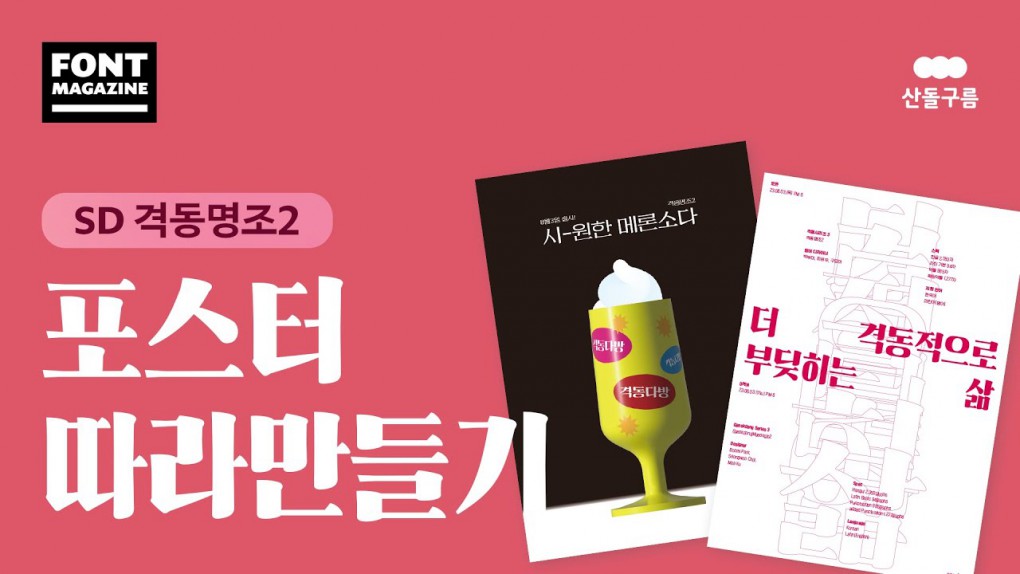
「SD 격동명조2」 출시 기념, 포스터 만들기 윗미~
‘격동’이라는 단어에서부터 가슴이 웅장해지는 분들, 많으시죠?
8월의 시작과 함께 반가운 소식을 전해드려요. 바로 「SD 격동명조2」 출시 소식입니다.
산돌 『격동』 시리즈로 불리는 격동고딕, 격동굴림, 격동명조 3총사는 지난 10년간 꾸준히 많은 분들의 사랑을 받아왔는데요, 「SD 격동명조2」의 출시로 드디어 10년간의 격동 시리즈를 완성하게 되었어요.
격동 시리즈의 완성이라니, 평범하게 소개할 수 없군요!
「SD 격동명조2」는 기존의 레귤러에서 15종 웨이트로 확장이 된 폰트로, 다른 그래픽이나 이미지가 추가로 필요하지 않을 정도로 폰트 자체의 디테일들이 살아있는데요, 이번 레터에서는 「SD 격동명조2」 를 활용한 그래픽 디자인 꿀팁에 대해 이야기해 보겠습니다. 폰트 자체의 완성도도 물론 중요하지만, 폰트를 실제로 사용했을 때 디자인에 잘 녹아드는지도 중요하니까요
일러스트레이터를 ‘잘’ 사용하는 꿀팁도 얻어 가세요.
복고풍의 느낌을 주면서도, 동양적이고, 실험적인 느낌을 동시에 가지고 있는 「SD 격동명조2」의 매력을 200% 살린 두 가지 포스터를 만들어봤는데요, 단순한 폰트 소개 영상이 아니랍니다. 그리드 세팅, 오브젝트 잠금 등 따라 하기 쉬운 팁부터, 미러링, 블렌드, 3D, 맵핑까지! 현직 디자이너의 일러스트레이터 작업 꿀팁을 압축했어요.